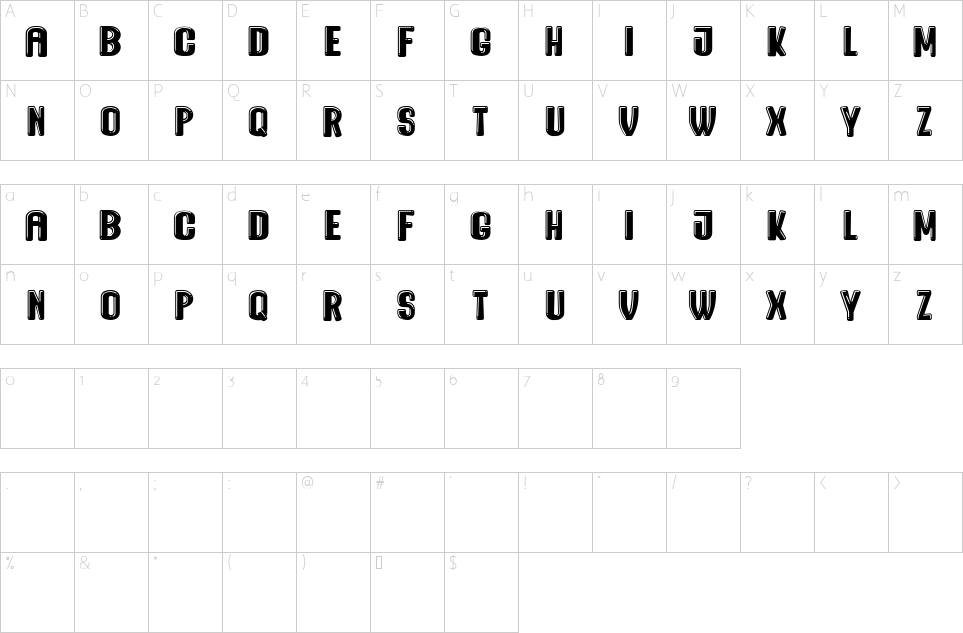
A Mercedes Font é uma elegante e moderna fonte que se destaca entre as opções gratuitas disponíveis. Desenhada pelo talentoso Vladimir Nikolic, esta font foi criada para atender aos designers e fãs de estilo moderno que procuram uma alternativa sofisticada aos sistemas de fontes padrão. Com um design limpo e sofisticado, a Mercedes Font é ideal para criar design gráfico moderno, websites, ilustrações e qualquer outro projeto que se beneficie de um visual clean e de alta qualidade. Esta font tem sido baixada 4,453 vezes, indicando a sua popularidade e valor como uma opção de fonte gratuita. Se você está buscando uma fonte moderna e elegante para seus projetos, a Mercedes Font é uma excelente escolha.